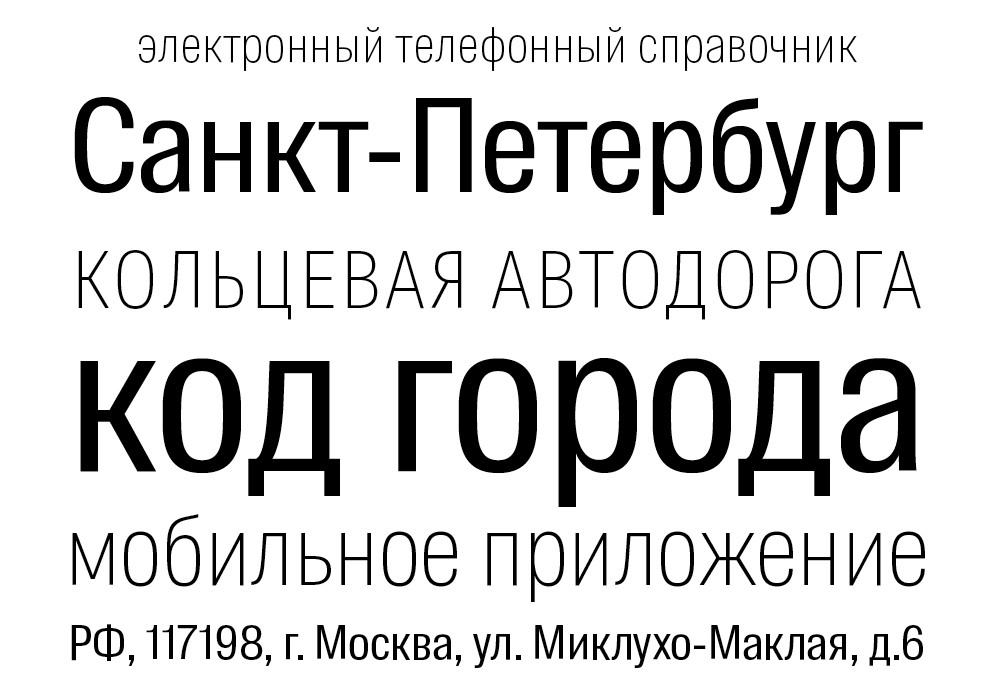
5. Интересных кириллических шрифтов очень мало
Хочу вас разочаровать, но и это миф 🙂 Только полюбуйтесь, какая библиотека на сайте CreativeMarket: https://goo.gl/hMnujz. Ещё, я очень люблю искать новинки на MyFonts: https://goo.
gl/iCG9P6 У него есть забавная функция — просмотр шрифта на примере вашего текста. Вы вбиваете свое имя или название бренда, и получаете демо шрифта!
Как вы заметили, хорошие шрифты стоят денег. Точно так, как дизайнерская одежда или картины, шрифты тоже были придуманы и кем-то созданы. Это не просто товар, шрифты — это искусство. Я не сторонница пиратских сайтов, которые грабят талантливых ребят. Таких, как мы с вами. Представьте, как обидно людям, которые годами создают нечто прекрасное и нужное, а через несколько дней видят свое детище на уродливых, мигающих баннерами пиратских сайтах, раздающих его бесплатно… Это дико, и я прошу уважения к художникам. На самом деле, в этом кроется гигантская экономическая проблема. Люди не могут и не хотят покупать то, что можно украсть, поэтому малый бизнес не развивается. Общество не развивается. Я честно покупаю приложения, шрифты, изображения и другие штуки, которые нужны для моей работы.
И всё же, если шрифт очень приглянулся, а цена никак не вписывается в бюджет, я предлагаю вам объединить усилия с друзьями и купить шрифт совместно. Если будут желающие, я соберу голоса в рамках нашего проекта, и мы сможем приобрести 3-4 новых шрифта на сезон!
* * * На этом всё 🙂 Надеюсь, вам было интересно, а ваш контент станет ярче!
С любовью к вам и шрифтам,
автор блога
Лена Бобрышева
Bureau Grot
Этот шрифт представляет собой красивый и чисто сложный стиль шрифта san serif, который предлагает привлекательные символы как с заглавными, так и с заглавными буквами. Он вдохновлен гротескным семейством шрифтов и позже был переработан, чтобы предложить более насыщенный шрифт.